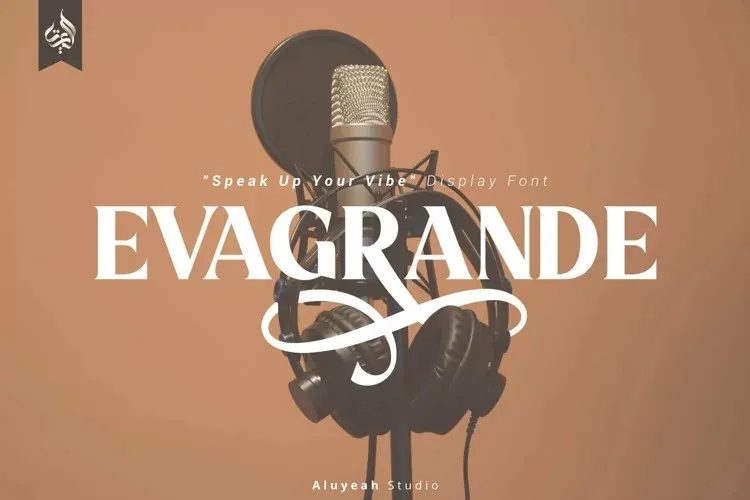
A Evagrande Font é uma nova fonte serif que inspira-se nos velhos tempos, mantendo no entanto sua aparência moderna. Desenvolvida pela Aluyeah Studio, essa fonte apresenta alternativas estilizadas tanto para letras maiúsculas quanto minúsculas, oferecendo um toque refinado e sofisticado à sua utilização. Ideal para aplicar em revistas, títulos de página, websites, anúncios, embalagens de produtos e projetos gráficos de qualquer natureza. Seja você criando material para a web ou impressão, esta fonte oferece um equilíbrio entre elegância clássica e modernidade vibrante que certamente impressionará seus clientes.